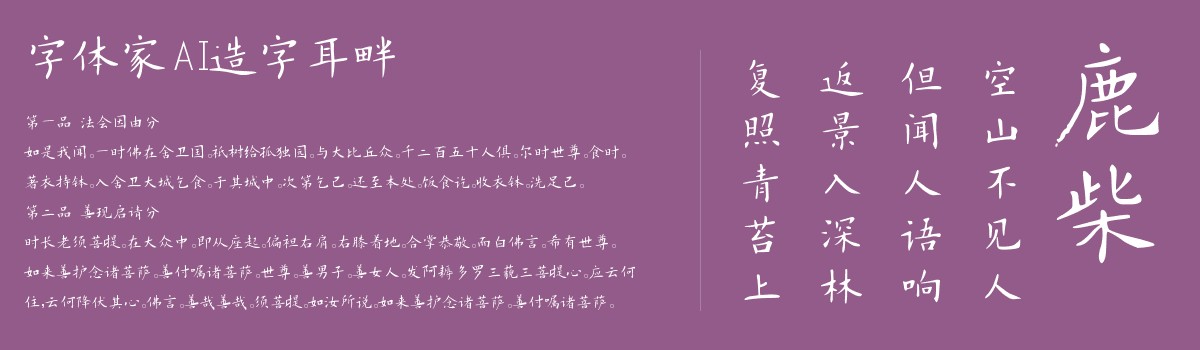
字体家AI造字耳畔
字体家AI造字耳畔是一款由字体家AI神笔造字生成的艺术字体,这款字体整体线条温润柔和,无尖锐棱角。笔画起收处圆润平滑,似晨露轻坠,无生硬顿挫。转折处皆以圆弧过渡,如溪流绕石,流畅自然。整体粗细均匀,如丝线织锦,疏密得宜。结构舒展不局促,部件比例协调,似微风拂柳,轻盈有度。兼具手写的亲和感与规范字的端庄,线条流畅如绸,触感柔和似棉,予人温暖、舒适的视觉体验,无攻击性,易读且耐看。适合用于一些广告标题、平面文案、海报标题、网页广告用字的编辑。